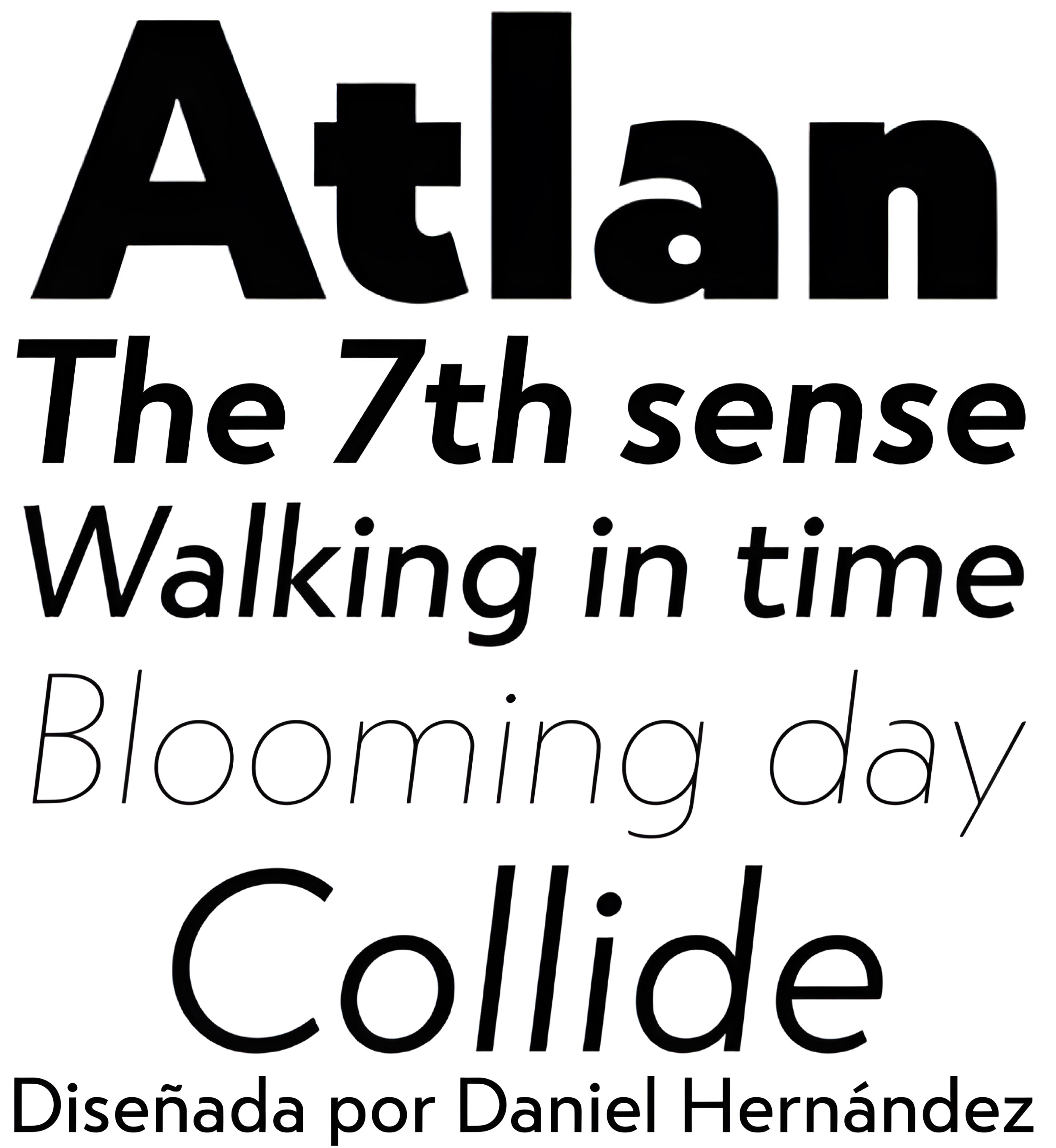
| Descripción | Atlan: un "spin-off" latino de los tipos de letra sin gracias geométricos clásicos. Recordando tipos como "Kabel" de Rudolf Koch y prestando atención a las necesidades actuales de diseño, nació "Atlan", un tipo de letra sencillo, elegante y atractivo. Este tipo de letra se basa en fuentes geométricas sin gracias muy expresivas de los años veinte. Nos planteamos el reto de reinterpretar estas características, sin perder expresividad, para crear un diseño funcional y versátil. El resultado es una fuente con características de visualización, muy adecuada para textos claros y de color uniforme. La familia ofrece una variedad de estilos, desde el elegante peso Thin -ideal para publicaciones y sitios web corporativos- hasta la variante Heavy (perfecta para logotipos y envases), que revela los elementos estilísticos del tipo de letra. |